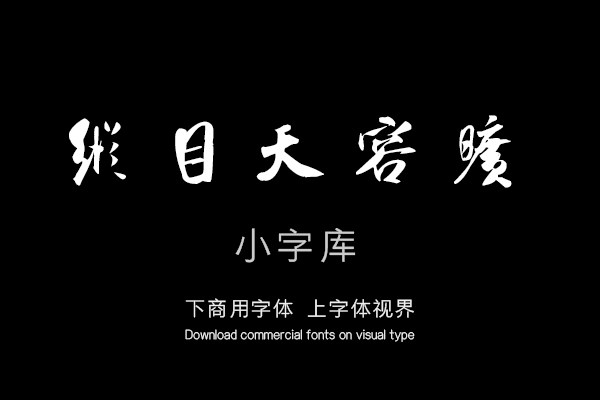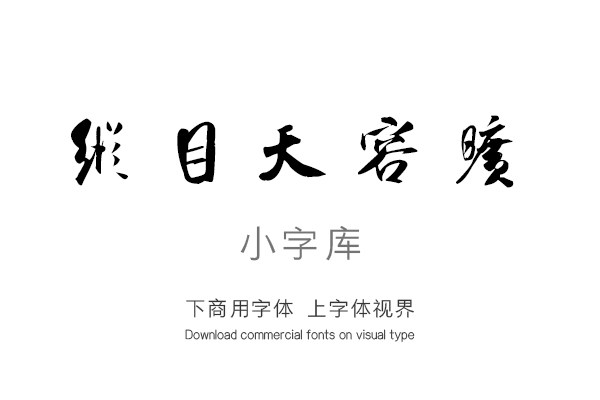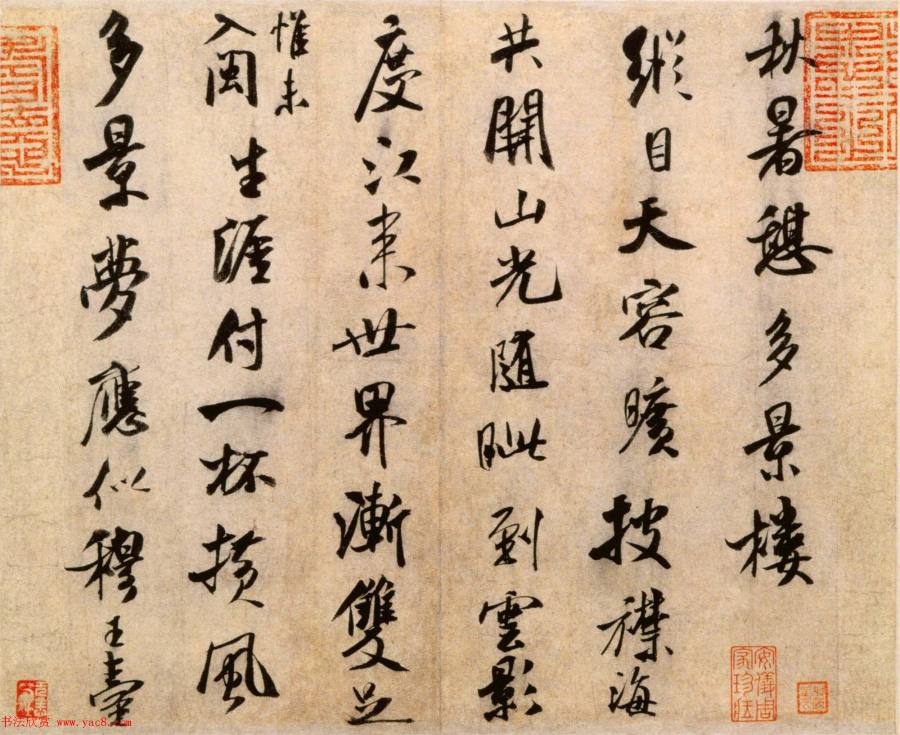
《汉标米芾秋暑憩多景楼帖》 小字库是由“汉标字库”耗时2年,收集古代知名书法家真迹制作而成,例如:《汉标米芾秋暑憩多景楼帖》是一款根据北宋米芾行书欣赏《秋暑憩多......单字授权
秋暑憩多景楼 纵目天容旷,披襟海共开。山光随眦到,云影度江来。世界渐双足,(入闽惟未)生涯付一杯,横风多景梦,应似穆王台。